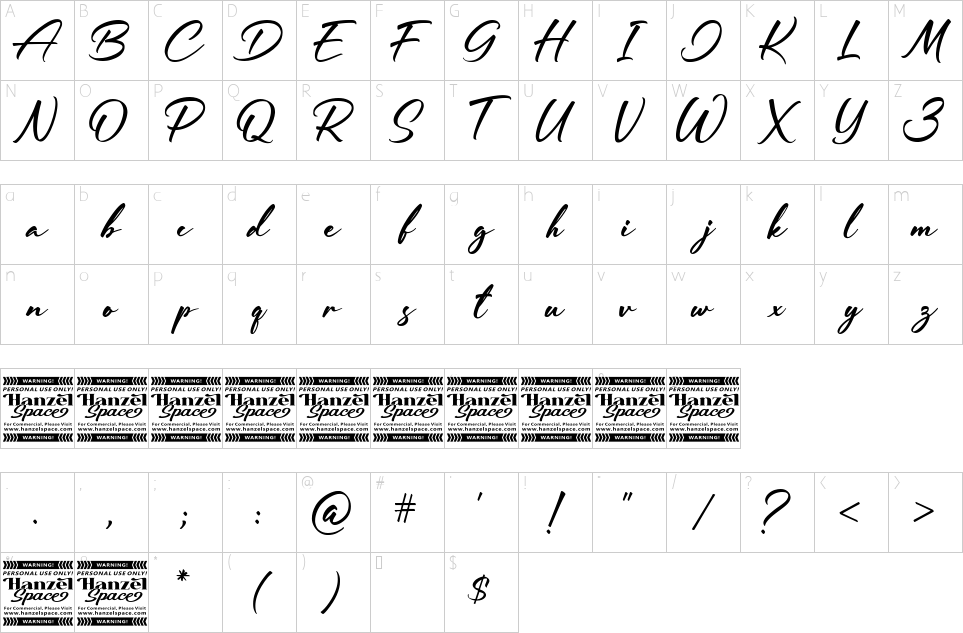
A fonte Jeasland Script oferece um estilo elegante e sofisticado, ideal para gráficos e designs de alta qualidade. Desenvolvida pela Hanzel Space, esta fonte é perfeita para aqueles que desejam adicionar um toque de originalidade aos seus projetos, seja em design gráfico, design de sites ou até mesmo em design de logotipos. Com seu traço elegante e versátil, Jeasland Script proporciona uma experiência única, permitindo que você personalize e personalize suas ideias de forma única. Esta fonte pode ser usada tanto no Windows quanto no Mac, tornando-a uma escolha agradável para designers de todo o mundo. Com 3,002 downloads, você pode estar certo de que é uma fonte altamente valorizada e usada por designers de todos os níveis. Experimente hoje e descubra por si mesmo por que Jeasland Script é uma fonte que todos os designers devem ter na sua lista de fontes.